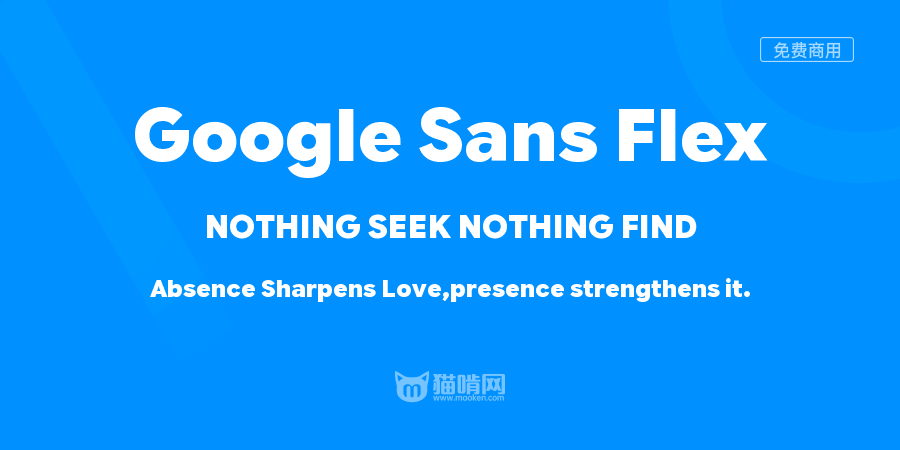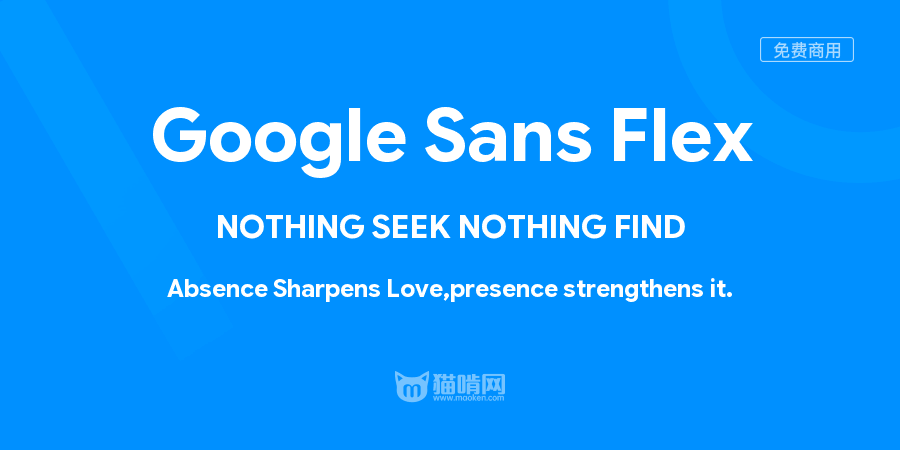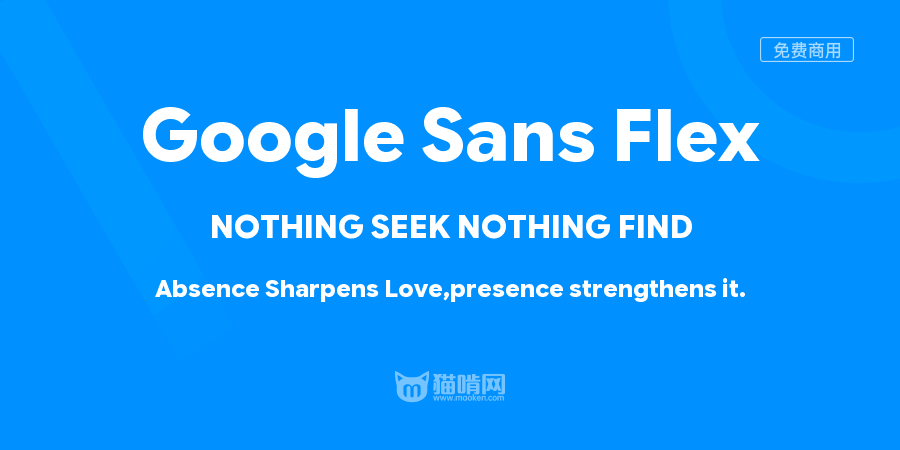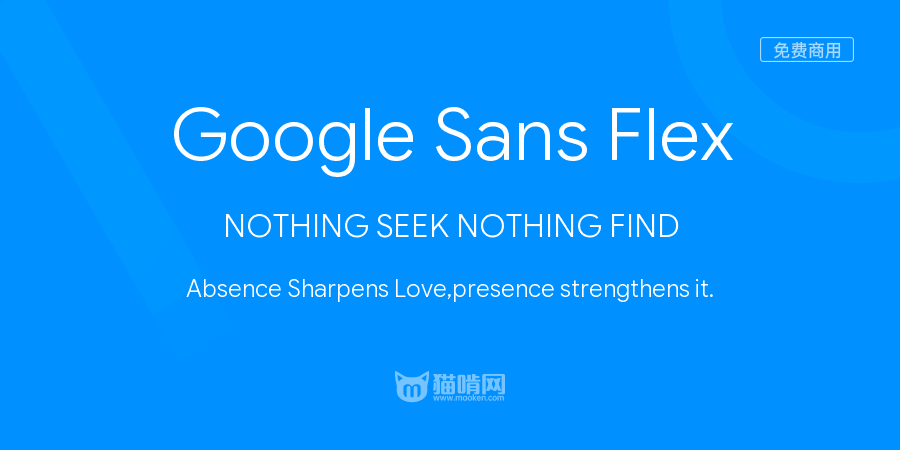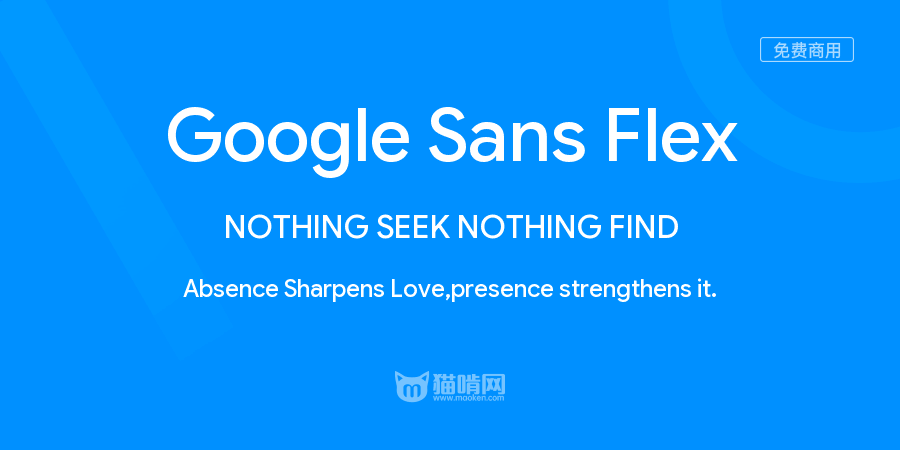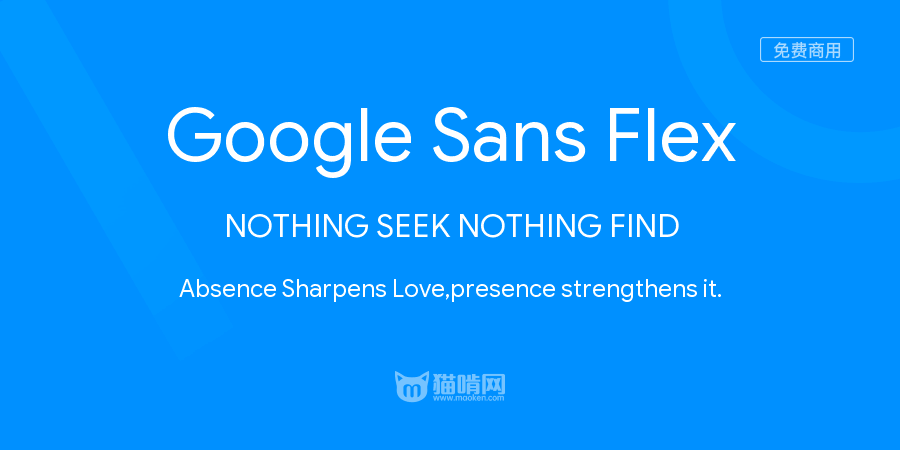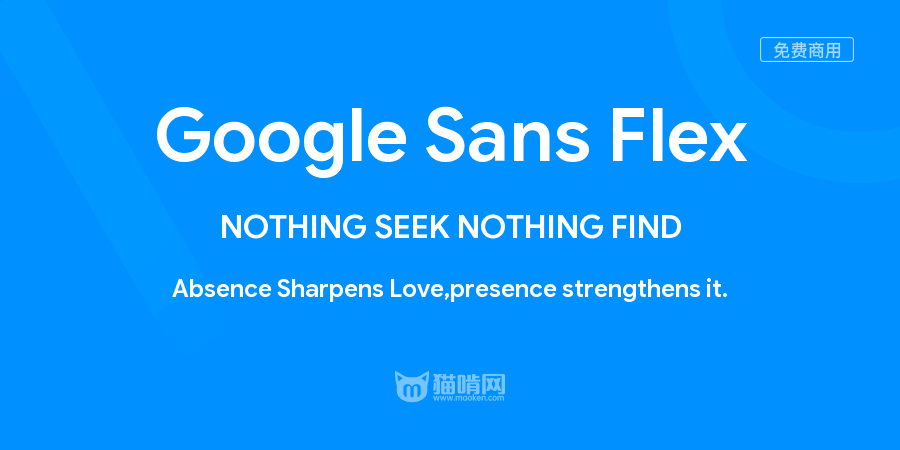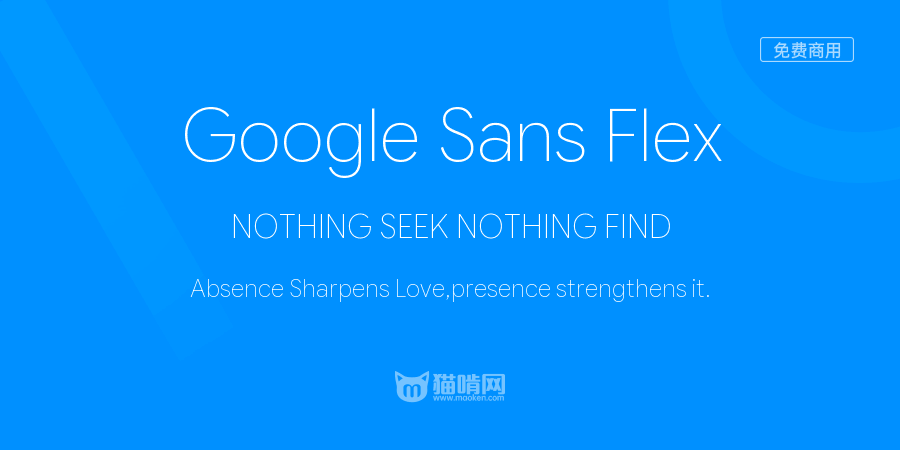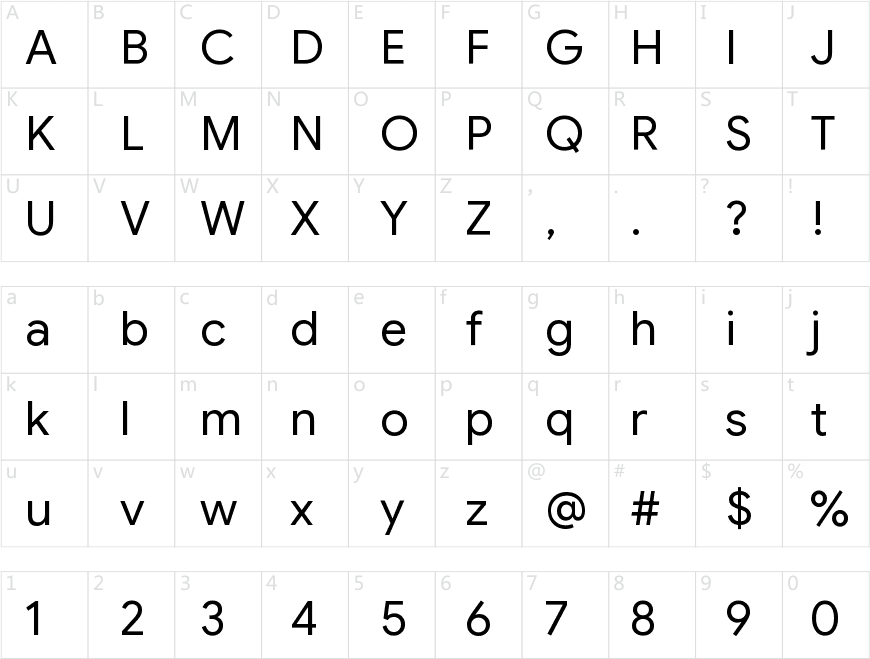
11 月 17 日,谷歌(Google)宣布开源了 Google Sans Flex 字体。用户可免费在 Google Fonts 字体网站下载和使用该字体,没有任何限制,包括商业场景。
根据官网给出的实例指南所描述,Google Sans Flex 字体有 9 种变体,包涵 Thin 100-Black 900 粗细范围,可更改字重、宽度、粗细、光学大小和笔画圆角等详细参数,带有英语、法语、德语等多种拉丁语言体系,但暂时没有中文字符。
因为Google Sans现在不只是谷歌的VI字体,还是自家的pixel系列设备的系统UI字体,这种情况下再搞什么限制都是形同虚设的(总不能说我分享个用自己的pixel手机截的图,结果就侵犯了谁的版权)
也在理,只是逗号有点不太好看,没有一撇简洁,也不是方块头,视觉上粗度比较浓